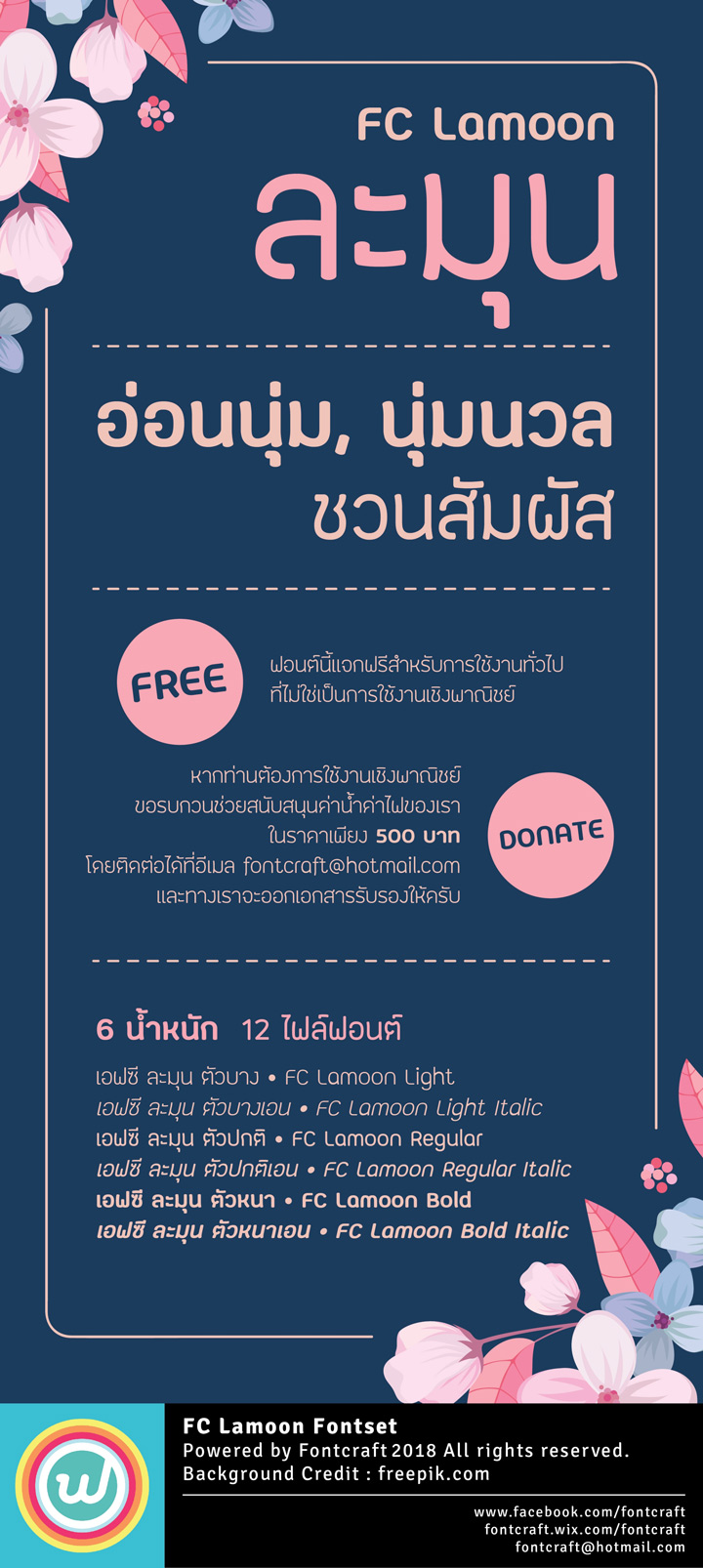
ละมุน (FC Lamoon)
เกิดขึ้นจากการออกแบบที่เน้นความนุ่มนวล ชวนสัมผัสผ่านสายตา ทำให้ผู้ใช้รู้สึกดี ผู้อ่านรู้สึกอบอุ่น
อีกทั้งยังเพิ่มน้ำหนักขึ้นมาจนครบ โดยมีให้เลือกใช้ทั้งตัวบาง, ตัวปกติ และตัวหนา รวมถึงตัวเอนของแต่ละน้ำหนัก เลือกติดตั้งได้ทั้งไฟล์ *.otf และ *.ttf รวมถึงทำ Hinting เบื้องต้นเพื่อให้การอ่านผ่านหน้าจออิเล็กทรอนิกส์ได้อย่างสวยงามยิ่งขึ้น
ข้อมูลคอมพิวเตอร์ฟอนต์: FC Lamoon (เอฟซี ละมุน)
ออกแบบและจัดทำโปรแกรมฟอนต์: Fontcraft
จุติพงศ์ ภูสุมาศ (Jutipong Poosumas)